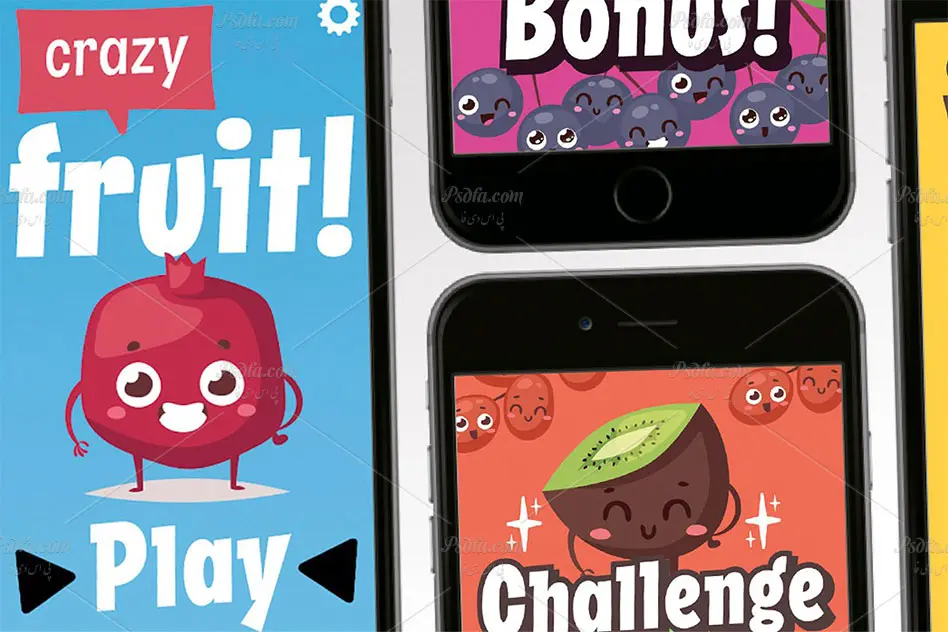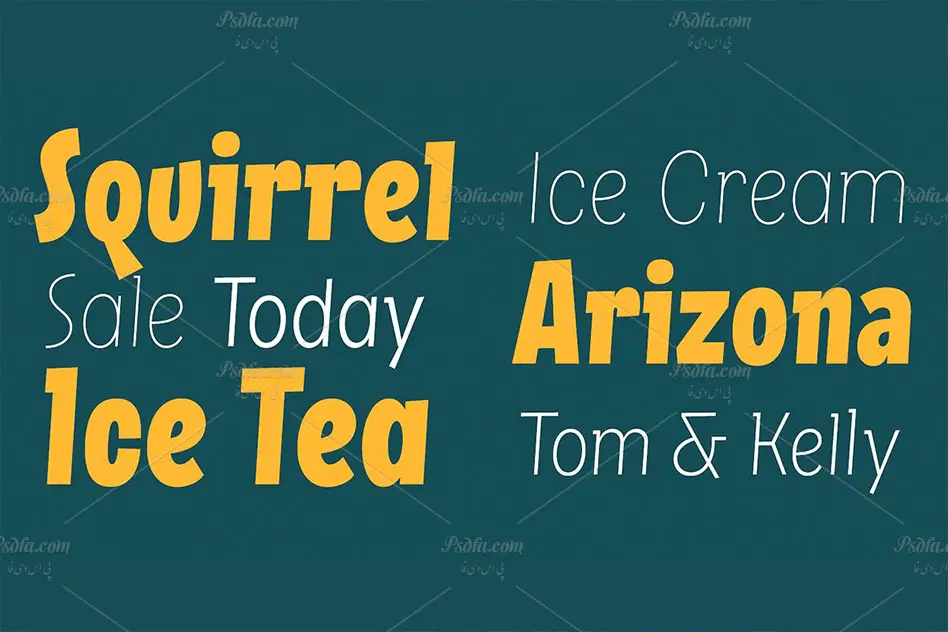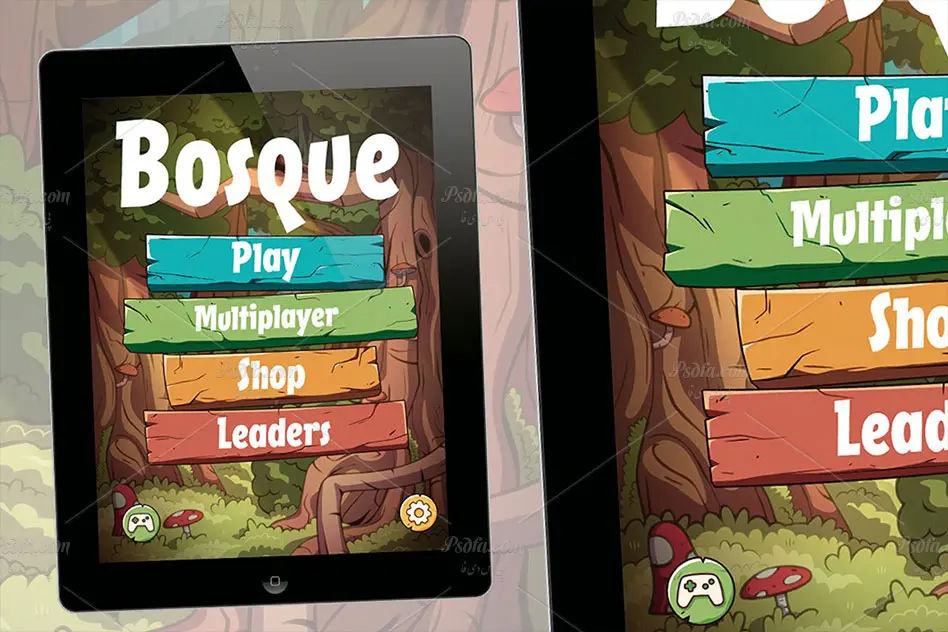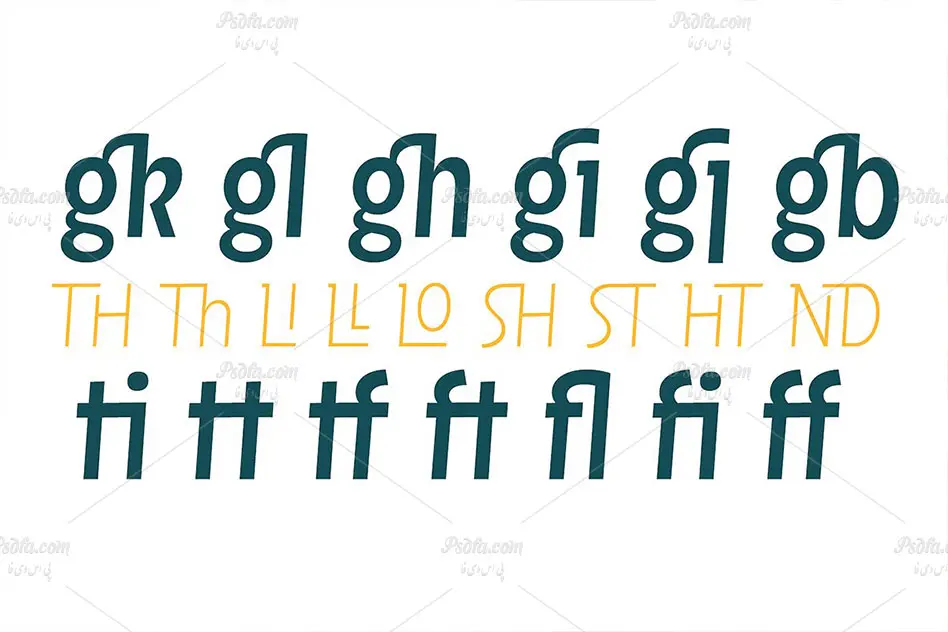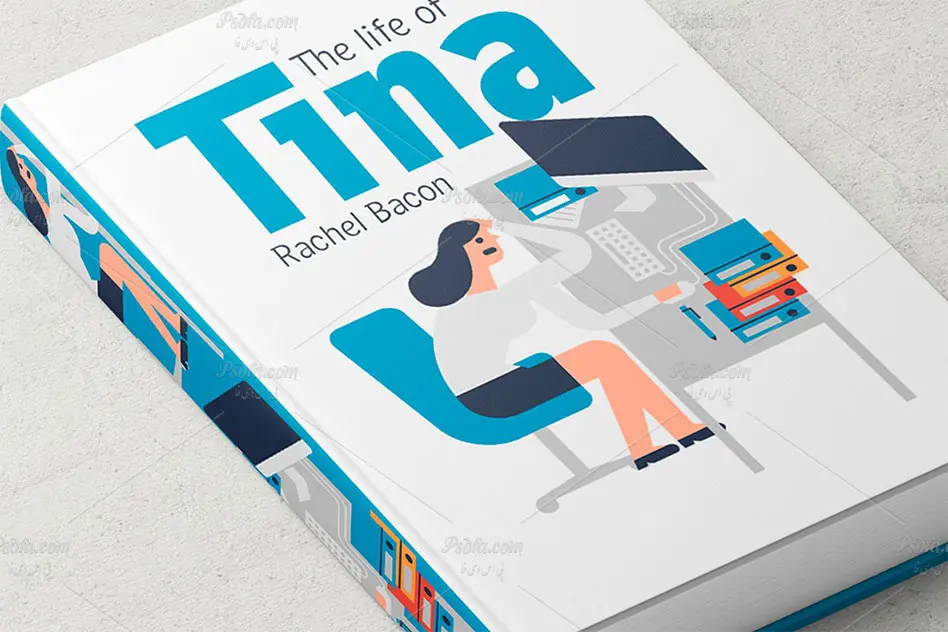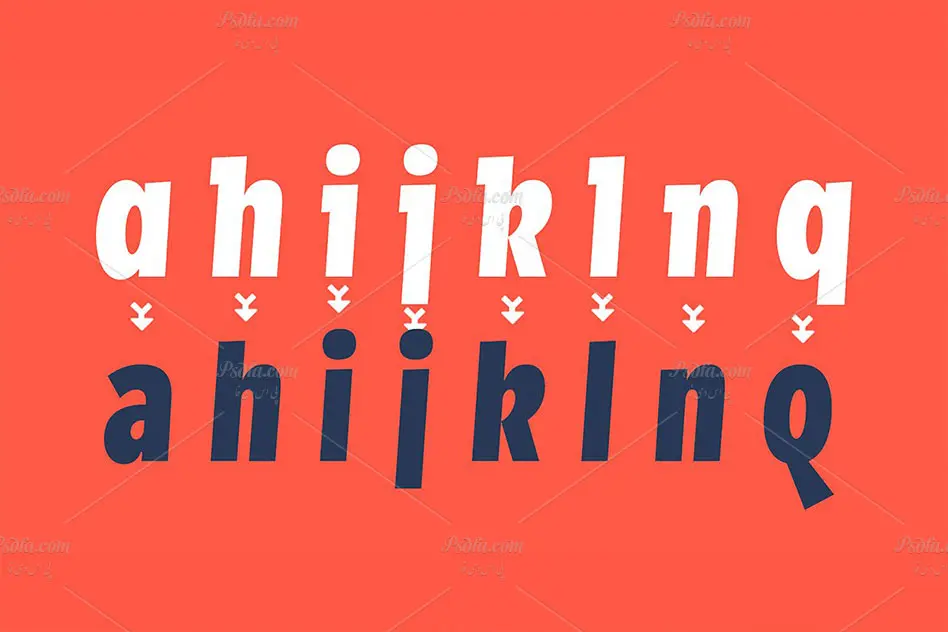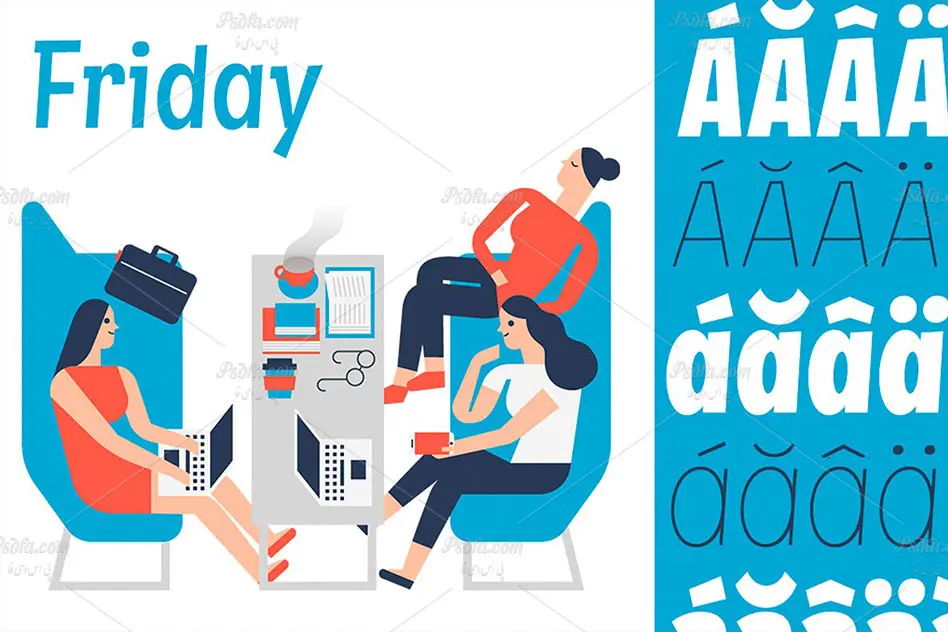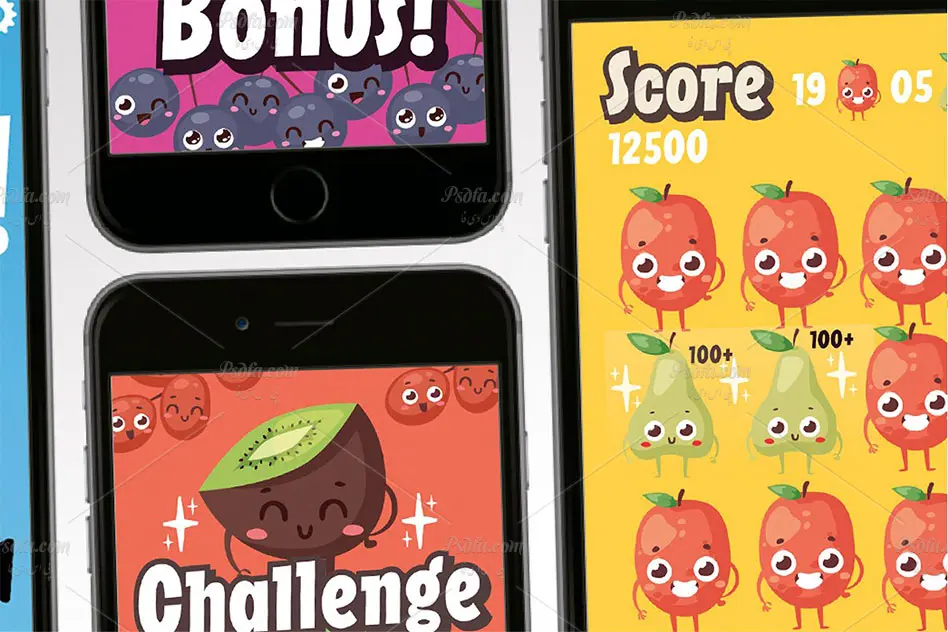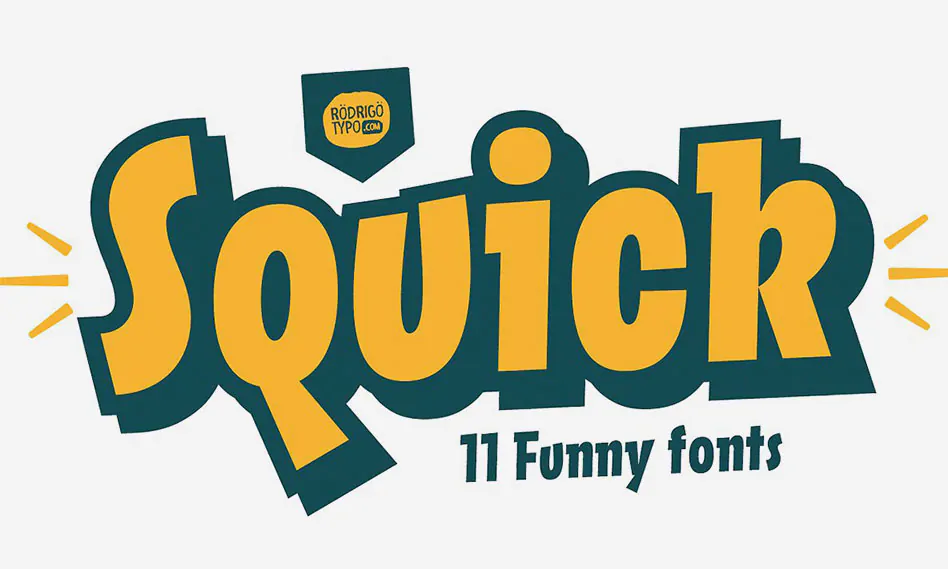
در این قسمت از سایت شاهد فونت انگلیسی فانتزی ، بامزه و کارتونی Squick مناسب جهت استفاده در طرح های گرافیکی می باشید. این فونت زیبا در قالب 11 فایل otf در سایت بارگذاری شده است که پس از نصب این مجموعه فونت در پوشه فونت های سیستم قادر به استفاده از آن ها در تمام نرم افزارهای گرافیکی و ویرایشگر متن از جمله نرم افزار فتوشاپ ، ایلاستریتور ، افترافکت ، مجموعه نرم افزار آفیس و … خواهید بود. فونت Squick در 11 وزن متفاوت طراحی شده است که بسته به نیاز خود می توانید از هر یک از سبک ها و یا وزن های این فونت در طرح های خود استفاده کنید. از این فونت زیبا می توان در ایجاد طرح های فانتزی و کودکانه همچون بازی های موبایلی ، طراحی انواع تقویم ، بروشور ، تراکت ، طراحی بر روی بسته بندی محصولات ، طراحی بر روی لباس و ایده های دیگر بهره گرفت.
- نام فونت : Squick
- شامل 11 فونت
- وزن : معمولی ، نازک ، خیلی نازک ، کلفت ، خیلی کلفت ، سایه دار ، متراکم و …